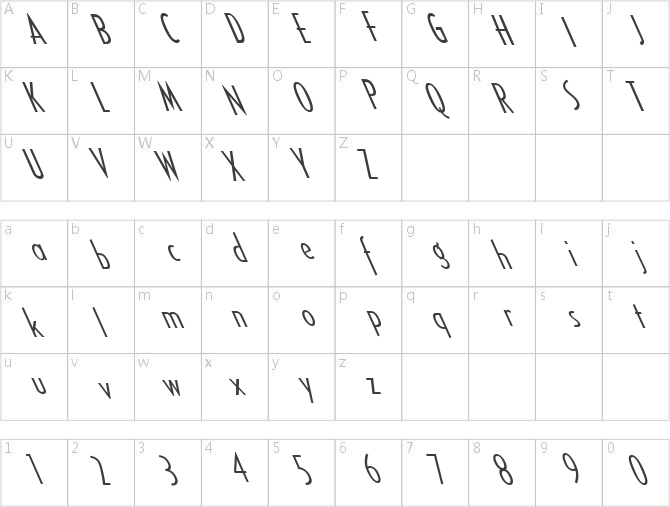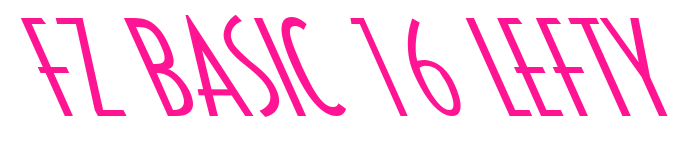
FZ BASIC 16 LEFTY 詳情頁(yè)
FZ BASIC 16 LEFTY字體字庫(kù)是一款讓人賞心悅目、百看不厭的英文字體,適合各類(lèi)廣告和產(chǎn)品包裝設(shè)計(jì)應(yīng)用,字體大小0.03MB,格式為ttf字體,上傳用戶是晴朗,作者/版權(quán)方為未知